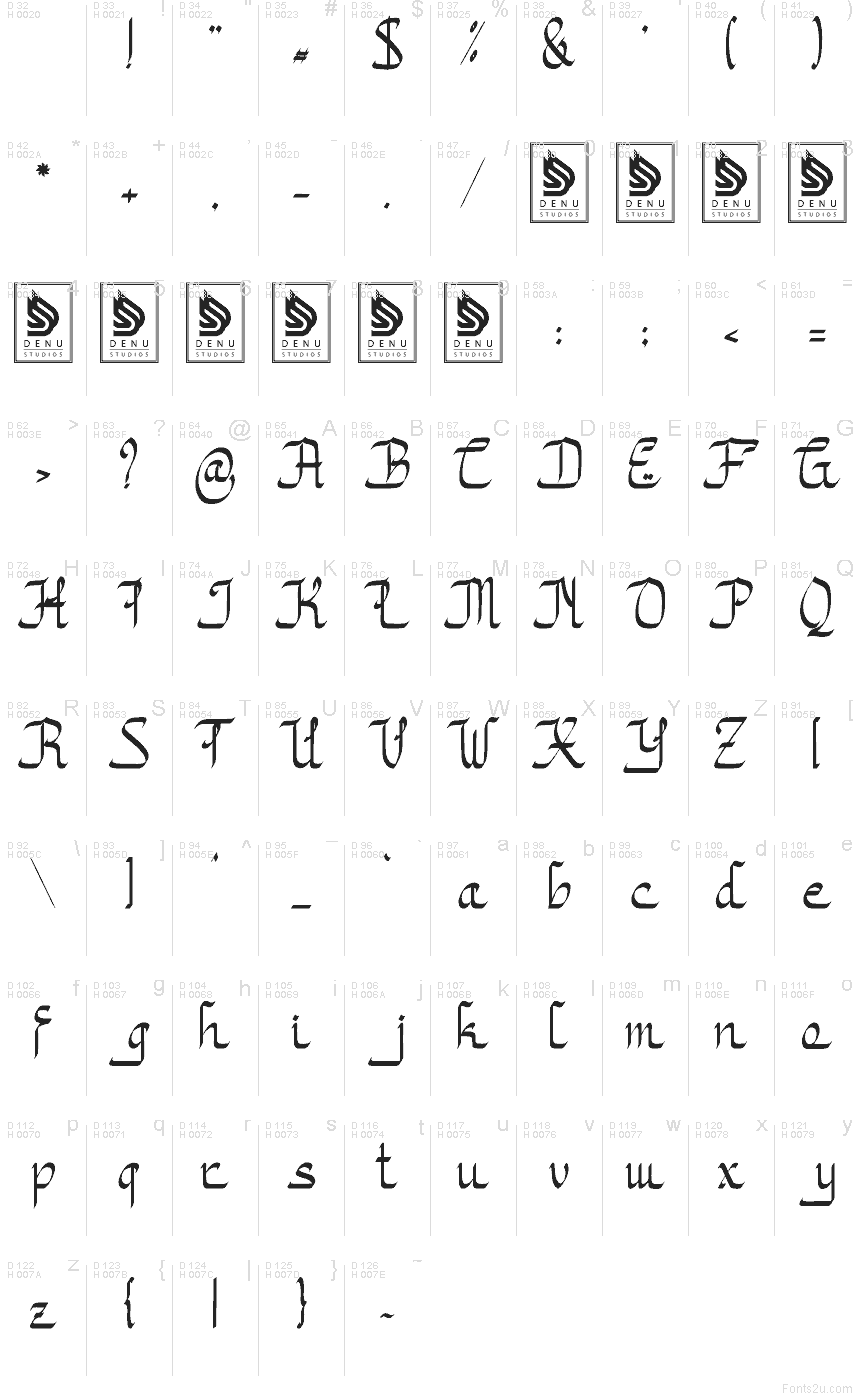
Mahyatti de Denustudios es una tipografía display gratuita inspirada en la caligrafía árabe, con un aire elegante y de otras épocas. Sus letras mezclan trazos verticales estrechos con terminaciones afiladas en forma de gancho, lo que confiere a las palabras un aspecto fluido y ligeramente ceremonial, mucho más allá de una simple escritura a mano.
Esto hace que Mahyatti tenga un lugar natural en el branding de perfumería, identidad de restaurantes, portadas de libros, carteles y packaging que buscan un toque dramático. Como tipografía gratuita, también funciona perfectamente en titulares editoriales, títulos de crédito y bocetos de logos, especialmente cuando buscas evocar una esencia de Oriente Medio sin llegar a ser puramente ornamental.